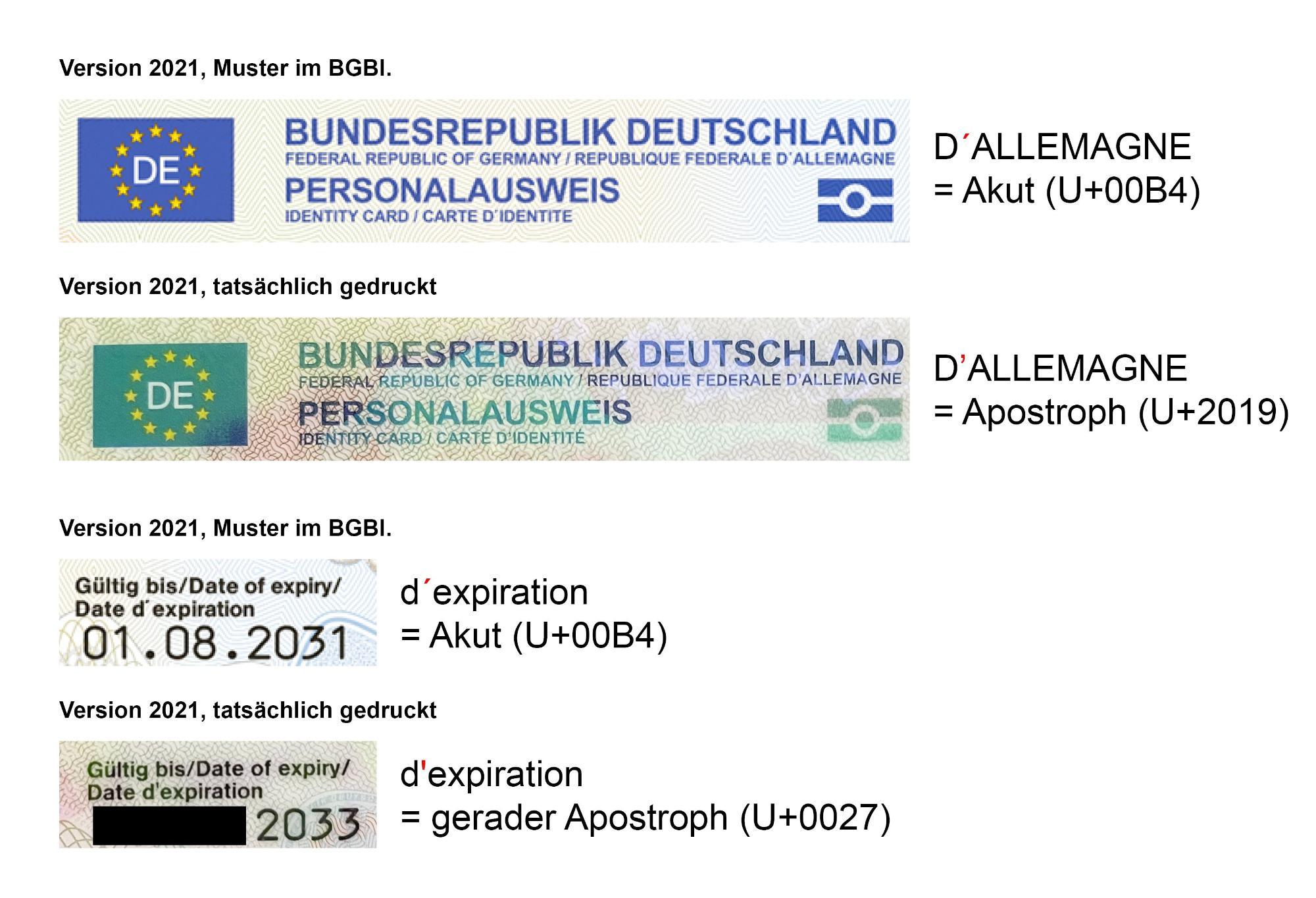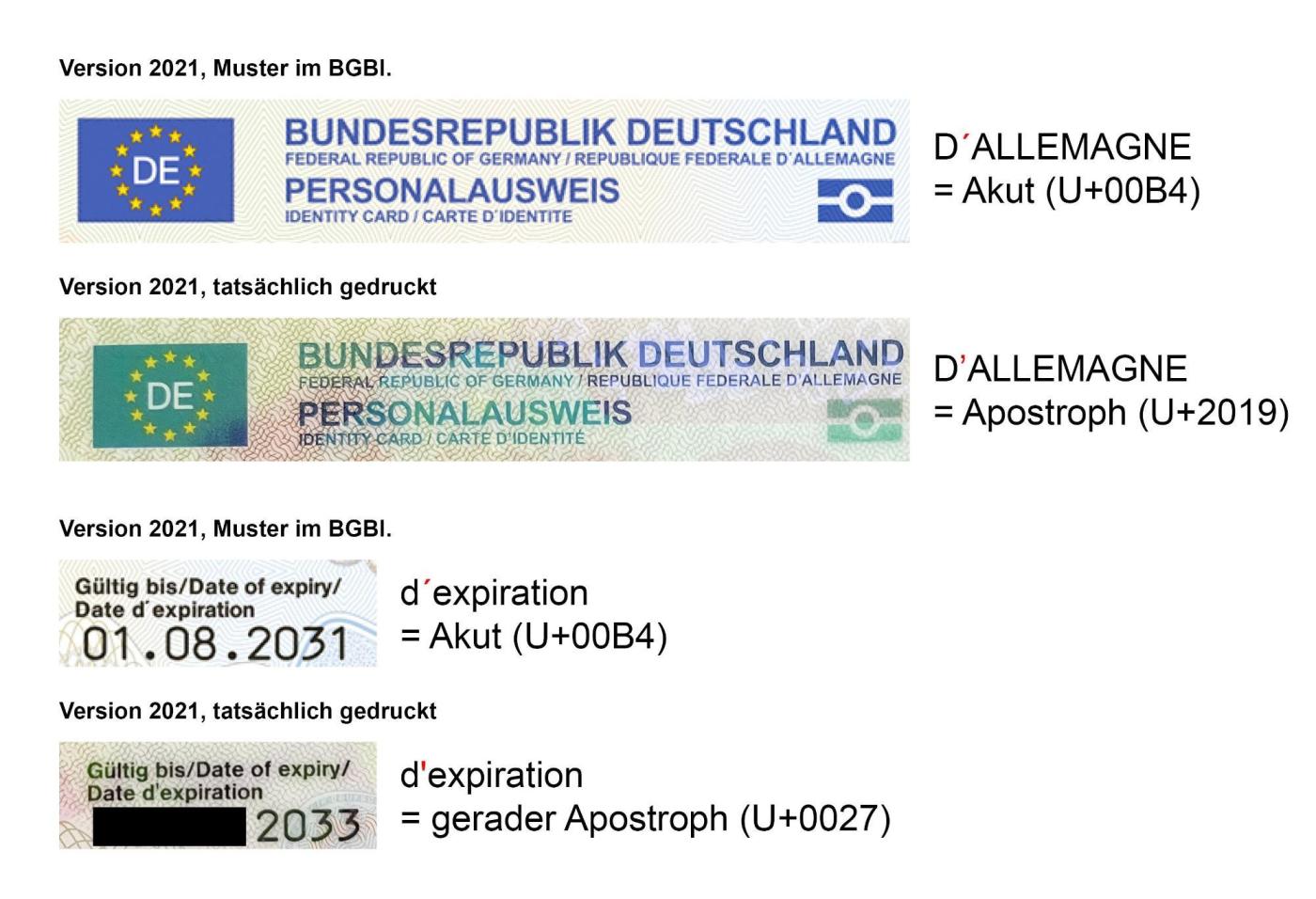
Schlechte Typografie beim Personalausweis?
beim Betrachten meines neuen Persos fiel auf, dass das Apostroph in der französischen Übersetzung uneinheitlich ist. Ich konnte die Schrift nicht eindeutig identifizieren (irgend etwas zwischen Arial und Helvetica, eine Eigenentwicklung?), weswegen eine genaue Glyphenzordnung nicht ganz so einfach für mich ist, aber ich habe es trotzdem mal versucht.
Betroffen ist die Überschrift sowie das Gültigkeitsdatum. Interessanterweise unterscheidet sich die gedruckte Version auch vom Muster, das im Bundesgesetzblatt abgedruckt ist. Hier wurden nachträglich also noch Änderungen vorgenommen.
Bei einer Institution wie der Bundesdruckerei hätte ich erwartet, dass auf solche Details geachtet würde. Was sagen die Experten: Fehler oder bloß schlechter Stil?
Ich würde mal sagen: Absicht. Denn auch die Guillochen sind anders* – wahrscheinlich wird man noch mehr minimale Abweichungen finden, wenn man ganz genau sucht. Soll halt niemand das Bild im Bundesgesetzblatt als Vorlage hernehmen. ;-)
*) … auch das Biometrielogo hat eine andere Farbe …
Keine Ahnung, aber laut diesem Dokument (PDF) heißt die Schriftart Unicode-Doc, verfügbar als Truetype in Regualar und Bold. Bis 2012 waren Arial und Courier (New) möglich.
UnicodeDoc wird nur von der Verwaltung für selbst ausgestellte Dokumente verwendet und ähnelt der Courier. U. a. die Aufkleber, die nach einem Umzug auf den Perso geklebt werden, werden damit beschriftet. Auf dem Perso selbst wird sie jedoch nicht verwendet.
Immerhin ist auf dem Ausweis der im Bgbl fehlende Accent in IDENTITÉ enthalten.
War mir gar nicht aufgefallen, gut gesehen! Das Design existiert ja schon seit 2021. Wäre interessant zu wissen, ob man das noch vor dem Druck der ersten Ausweise bemerkt hat.
Verwendete Schriften scheinen zu sein (bzw. sind sehr ähnlich): Arial (Überschrift), Helvetica Neue (Feldbeschriftungen), OCR-B (Ausweisnummer, Zugangsnummer, MRZ), unbekannte Eigenentwicklung (Personalisierung).
Zur Schriftart der Personalisierung kann ich folgendes beitragen: Es ist eine Festbreiten, Schreibmaschinenschriftart, die man bei elektrischen Schreibmaschinen der 80er, Anfang 90er Jahre findet. Herausstechend sind die Schweifungen bei den Nummern 3,5,6 und 9. Das macht die Schriftart ziemlich einzigartig. Nun gibt es 3 digitalisierte Schriftarten in dieser Form, die aber auch nicht ganz passen:
SV Basic Manual - Da passt die Ziffer 1 aber nicht die Ziffer 8.
Cubiculum - Kommerzielle Weiterentwicklung der SV Basic Manual. Auch hier das gleiche bei den Ziffern.
SaxMono - Ist mir dann noch bekannt. Hier passt zwar die Ziffer 8, aber nicht die Ziffer 1, die in Form eines kleinen "l" dargestellt wird.
Im übrigen gibt es bei keinem der Schriftarten das große ẞ - Wird aber auch dem Personalausweis verwendet.
Cubiculum - Kommerzielle Weiterentwicklung …
Kommerzielle Weiterentwicklung? Da musste ich jetzt doch bisschen schmunzeln, jene wird als "Bold Italic" vermarktet:
Es würde mich doch arg wundern, wenn die Bundesdruckerei auf einen frei verfügbaren Font zurückgreift, das würde die Fälschungssicherheit doch arg auf Hinterhofniveau senken.
Ebenso wie "UnicodeDoc" vom BMI bei zwei Berliner Schriftgestaltern in Auftrag gegeben wurde, wird das ähnlich mit der Perso-Schrift geschehen sein. Es gibt ein paar ähnliche Fonts (ein Beispiel wäre noch T-Star Mono Round, die aber nicht mehr vertrieben wird), aber als Normalsterblicher kommt man nicht an das Original.
Die gleiche Schrift wird übrigens auch auf den elektronischen Dienstausweisen des Bundes verwendet, wer die zugehörigen Minuskeln mal betrachten möchte. Die Muster sind als Anlage zur Gemeinsamen Geschäftsordnung der Bundesministerien öffentlich zugänglich.
das ist wirklich elend schlampig: bei den versalien, die, wenn nötig, immer auch accents haben sollen (>>> https://www.academie-francaise.fr/questions-de-langue#5_strong-em-accentuation-des-majuscules-em-strong), fehlen diese -- nur IDENTITÉ hat einen. bei der RÉPUBLIQUE FÉDÉRALE dagegen fehlen sie.
so oder so: mal setzen, mal nicht, ist jedenfalls seltsam.